Mit Opentype-SVG lassen sich die Glyphen einer Schrift mit SVG-Grafiken darstellen. Somit werden Farben und Verläufe in den Buchstaben möglich und Schriften können wie mit einem Pinsel geschrieben wirken. Hier kommt eine Auswahl mit kostenlosen SVG-Fonts, die uns in letzter Zeit aufgefallen sind.
SVG-Fonts haben den Vorteil, dass man direkt beim Schreiben verschiedene Farben, Verläufe oder Transparenzen in den Buchstaben erzielt. Spezielle Effekte, die man womöglich anderweitig nur mit erheblicher Nachbearbeitung erzielen kann, sind hier also von vornherein schon mit drin. Das macht sich vor allem bei handgeschriebenen Schriftarten bemerkbar. Es gibt allerdings auch einen kleinen Wermutstropfen: Auf Font-Hinting muss man verzichten. Das fällt allerdings bei den großzügigen Diplay-Fonts oft nicht ins Gewicht und lässt sich bei Bedarf von Hand nachbessern. Mehr zum Thema Opentype und SVG kann man übrigens in der Übersicht der Fontformate nachlesen.
Wie auch immer, hier kommen jetzt zehn sehenswerte SVG-Fonts, die mit handgeschriebenen Effekten aufwarten und sich zudem noch kostenlos herunterladen lassen. Viel Vergnügen beim Ausprobieren!
MacBeth Free SVG-Font
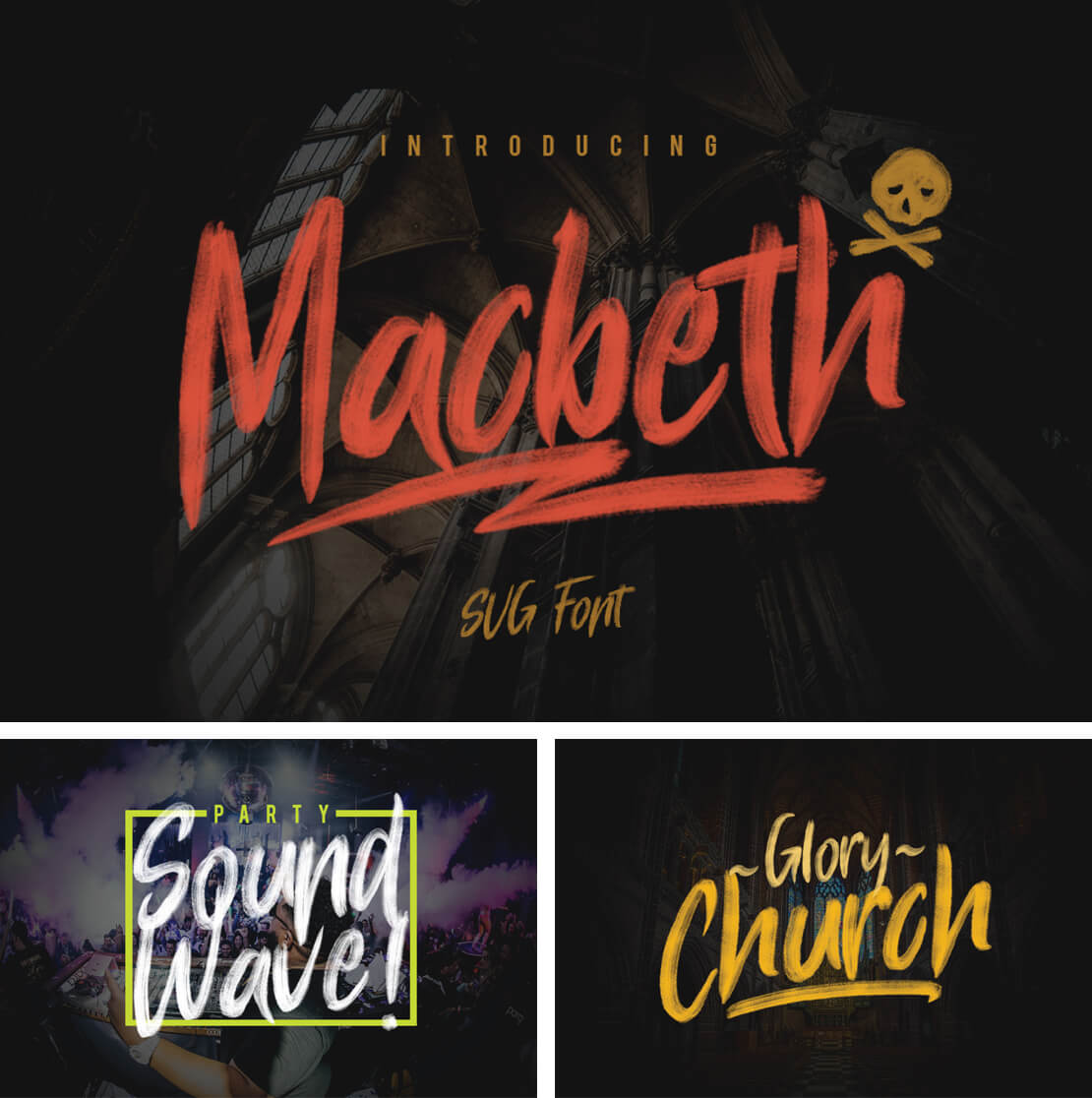
Viele Details werden bei diesem SVG-Font sichtbar, wenn man ihn besonders groß verwendet. Enthalten sind neben den Buchstaben auch Zahlen, Satzzeichen und einige Extra-Symbole. »MacBeth« gibt es kostenlos zum Downloaden. Die Schrift darf in privaten und kommerziellen Projekten Verwendung finden.
Brixton Handprinted Font
Dieser Font sieht aus, als wäre er mit Letterpress-Technik realisiert worden. Er besteht aus den Varianten »Wood« und »Lead«. Erstere ist zum Ausprobieren gedacht und steht dementsprechend kostenlos zum Herunterladen zur Verfügung. Das vollständige Paket gibt es zudem bei YouWorkForThem.
Nolan Font
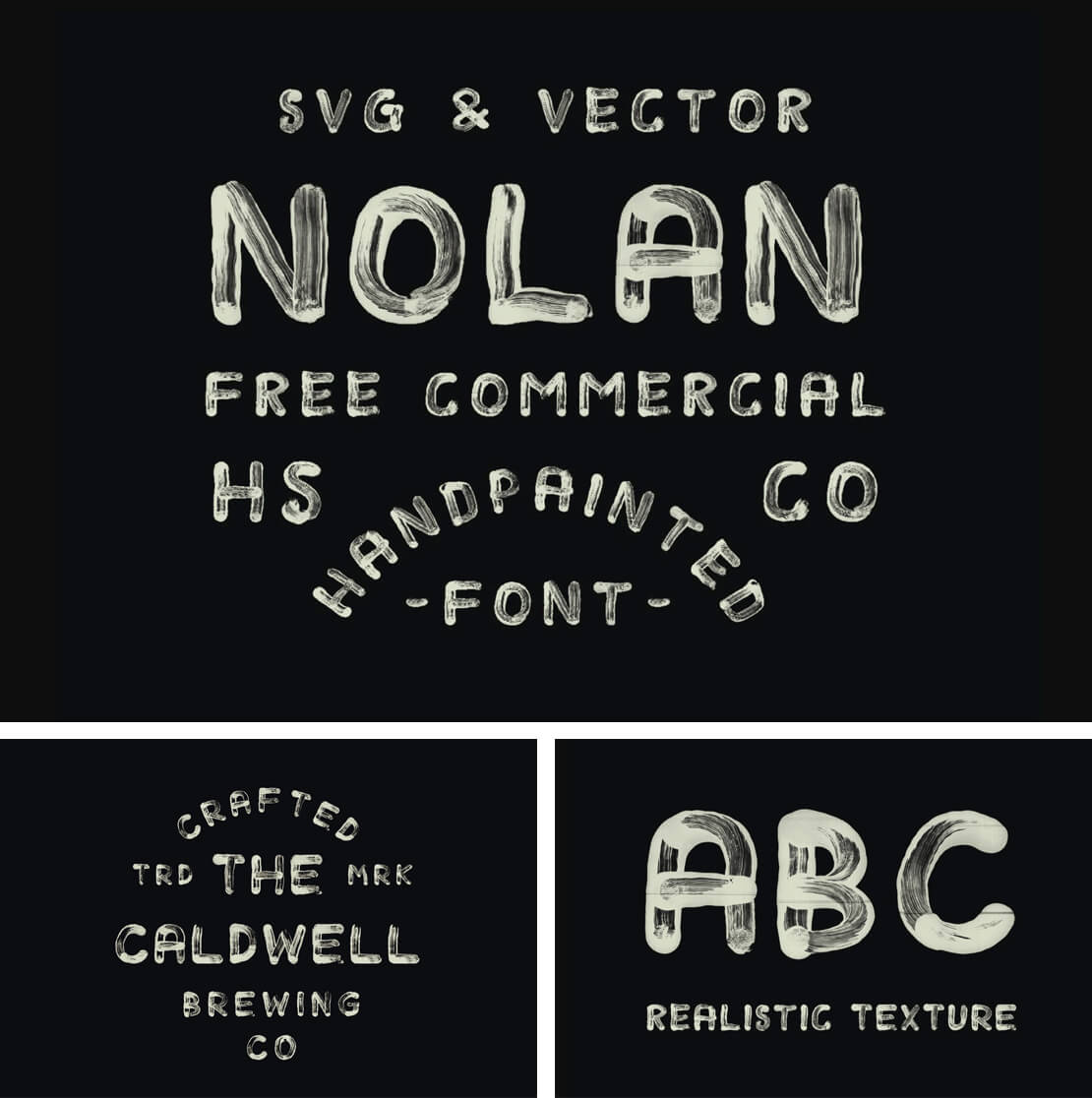
So richtig handgemacht wirkt auch »Nolan«. Die Schrift mit ihren kräftigen Lettern darf kostenlos für kommerzielle Projekte verwendet werden. Zum Downloaden geht es hier entlang:
Lyon & Crest SVG Font
Viel Handarbeit ist anscheinend in die Ausarbeitung dieses SVG-Fonts gesteckt worden. Er besteht aus einer regulären Version und einer Variante in markantem Pinselstil. Mehr als 15 Ligaturen und alternative Zeichen gibt es zudem noch obendrauf. Die Fonts lassen sich ohne Anmeldung direkt von Pixelbuddha-Website laden:
Bafora Brush Svg Font
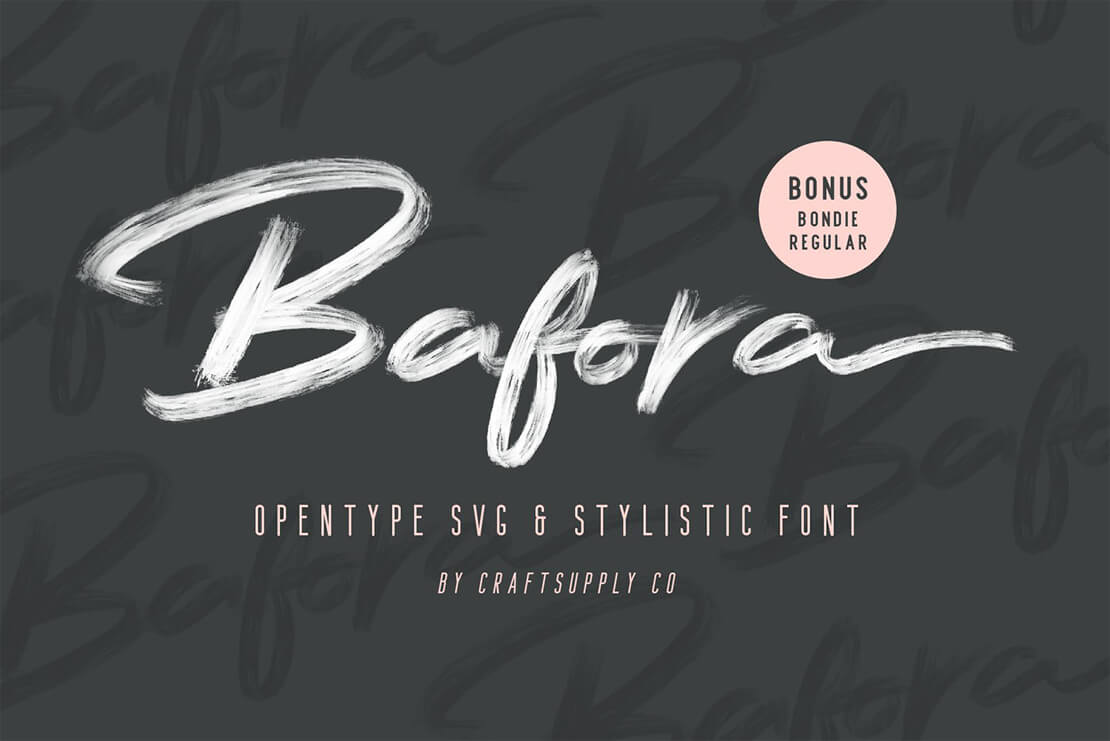
»Bafora« ist ein SVG-Font, der wie mit einem dicken Borstenpinsel geschrieben aussieht. Die kommerzielle Version* der Schrift enthält alle Glyphen. Bei dem für private Zwecke vorgesehenen Free-Font sind weniger Zeichen enthalten. Dafür lässt sich dieser kostenlos herunterladen und ausprobieren.
Hackney Handpainted SVG Font
Einen handgemalten Charakter bietet auch der Font »Hackney«. Dieser lässt sich am besten plakativ einsetzen, damit auch die feinen Details in den Buchstaben zur Geltung kommen. Auch hier gibt es eine kostenpflichtige* und eine kostenlose Version des SVG-Fonts:
Mr. Grieves Free Font
»Mr. Grieves« ist eigenwillig und hat Charakter. Ein expressiver, gemalter SVG-Font, der sich für Display-Zwecke verwenden lässt. Den unkonventionellen Style verdankt die Schriftart übrigens dem gleichnamigen Pixies-Song. Das Doolittle-Album von 1989 diente nämlich als Inspiration.
Strive Free Font
»Strive« wirkt wie mit einem dicken Pinsel von Hand geschrieben und macht besonders in großen Punktgrößen eine ansprechende Figur. Erst dann treten die Details in den Glyphen so richtig hervor. Der kostenlose SVG-Font ist für private Nutzung gedacht.
Drag Race SVG Marker Font
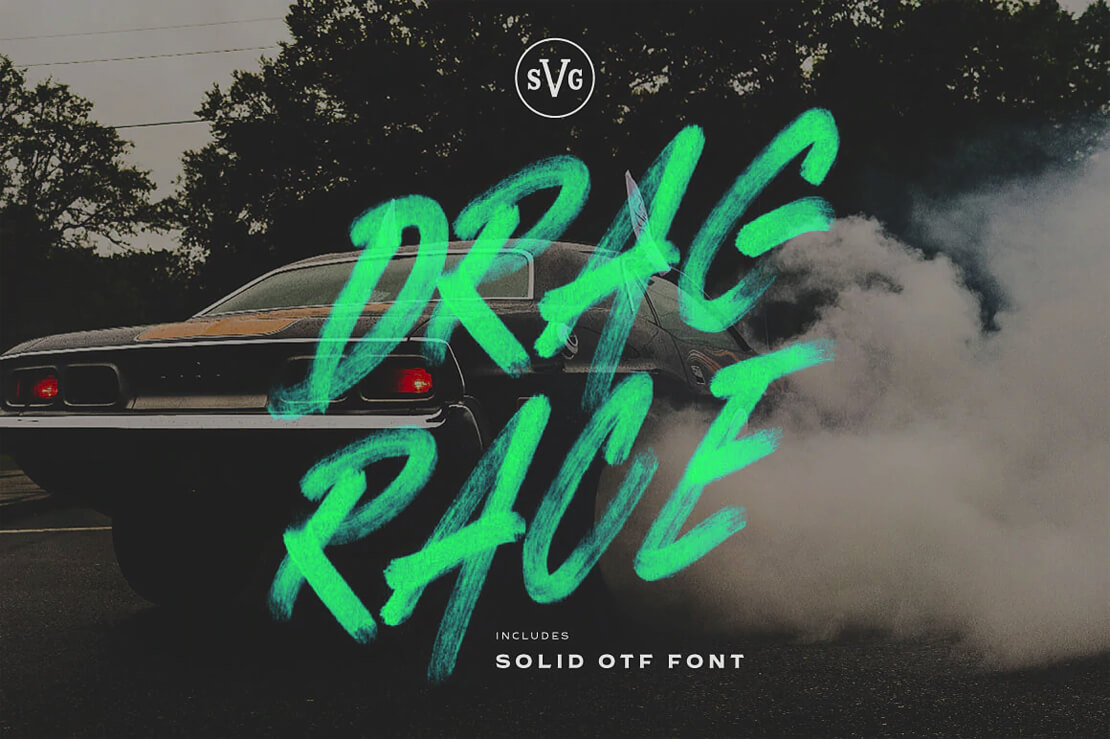
Auf die Plätze, fertig, los! »Drag Race« ist ein mit schnellem Pinsel geschriebener SVG-Font, der sich für Sport, Athletik, Autos und Co. eignet. Ein deutlich erkennbarer Transparenz-Effekt zieht sich durch alle Buchstaben.
Marker Mark SVG Font
»Marker Mark« ist ein Brush-Font, der wie von Hand mit einem Filzstift geschrieben aussieht. Die Schrift wurde tatsächlich zuvor auf Papier gezeichnet und anschließend in Photoshop weiterbearbeitet.